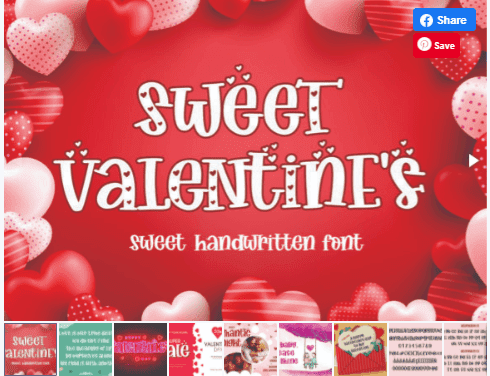
Название: Sweet Valentine's Font (2021)
Sweet Valentine’s - романтичный и приятный дисплейный шрифт. Используете ли вы его для творчества, цифрового дизайна, презентаций или изготовления поздравительных открыток - он идеален!